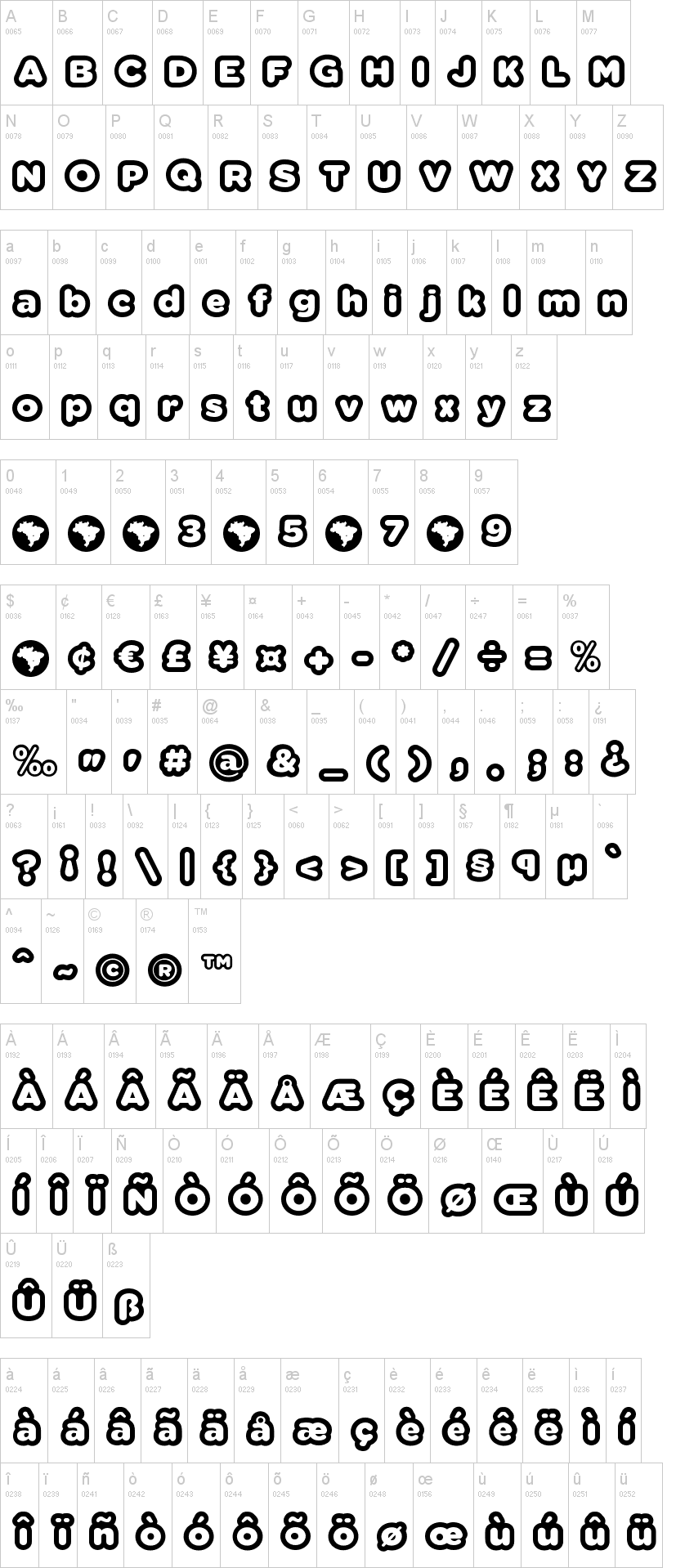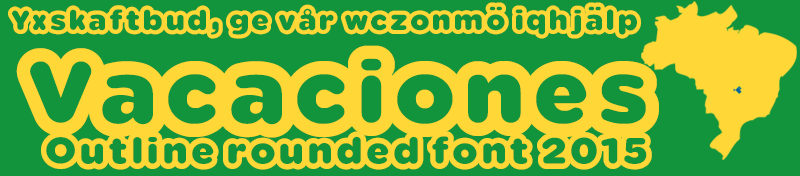
Note of the authorNueva tipografía vacacional 2015 de formas voluptuosas, gruesas y redondeadas. Fuente de talla baja de carácter amigable con ascendentes y descendentes cortos de fuerte contraste en las uniones de las astas, agradable y funcional para títulos y textos cortos o el diseño de carteles y posters.
New 2015 Holiday typography voluptuous, thick and rounded shapes. Font of stunting friendly character and falling short of strong contrast in the joints of the antlers, pleasant and functional for titles and short texts or designing posters and affiches.